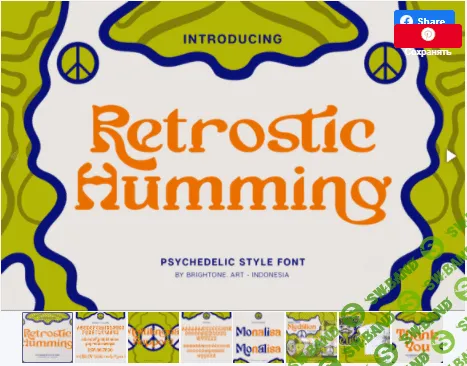
Название: Retrostic Humming Font (2022)
Retrostic Humming — это шрифт Psychedelic Hippie Display с потрясающим стилем. Используйте его, чтобы создать самый крутой логотип штамма, дизайн рубашки, дизайн сумки, этикетку, наклейку, брендинг для вашего бренда каннабиса и т. д.